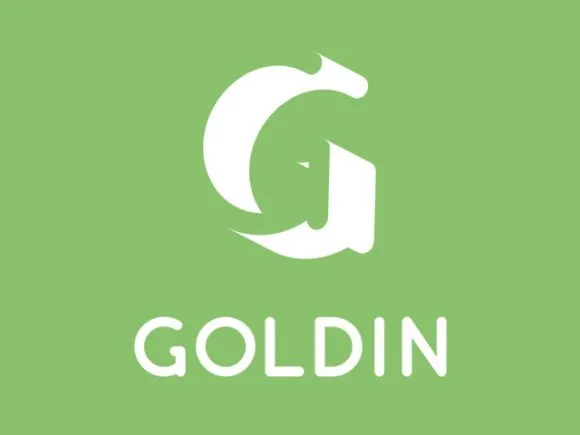
Aqui está uma descrição em português para a página de download da fonte ‘Goldin Typeface’, mantendo os requisitos fornecidos: Hamilton é o designer responsável pela inovadora fonte sans-serif chamada Goldin. Este projeto foi desenvolvido por Fabian Korn, um criativo gráfico oriundo do solo suíço. A fonte contém apenas letras maiúsculas e oferece dois pesos de negrito: leve e regular. Sempre buscando inovação no universo da tipografia, Hamilton criou uma alternativa perfeita para designers que valorizam a simplicidade e o modernismo. Com sua linguagem fluida e elegante, Goldin se destaca como um excelente recurso para qualquer projeto de design gráfico. Seja você um designer digital ou impressão, seja a sua marca ou a criação de uma peça editorial, a fonte ‘Goldin Typeface’ tem algo para complementar seu trabalho.